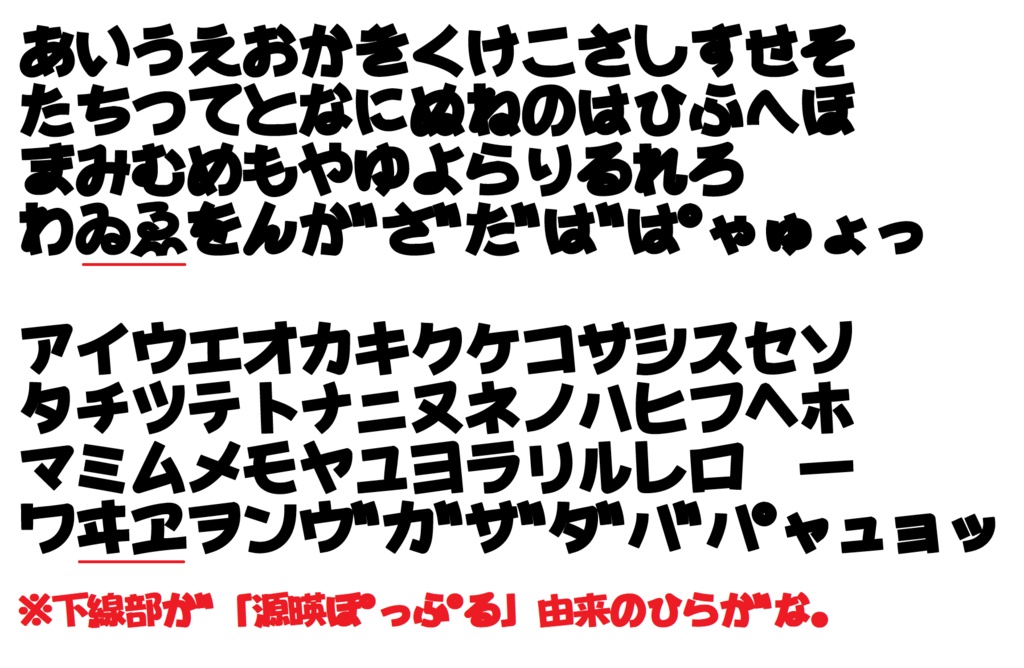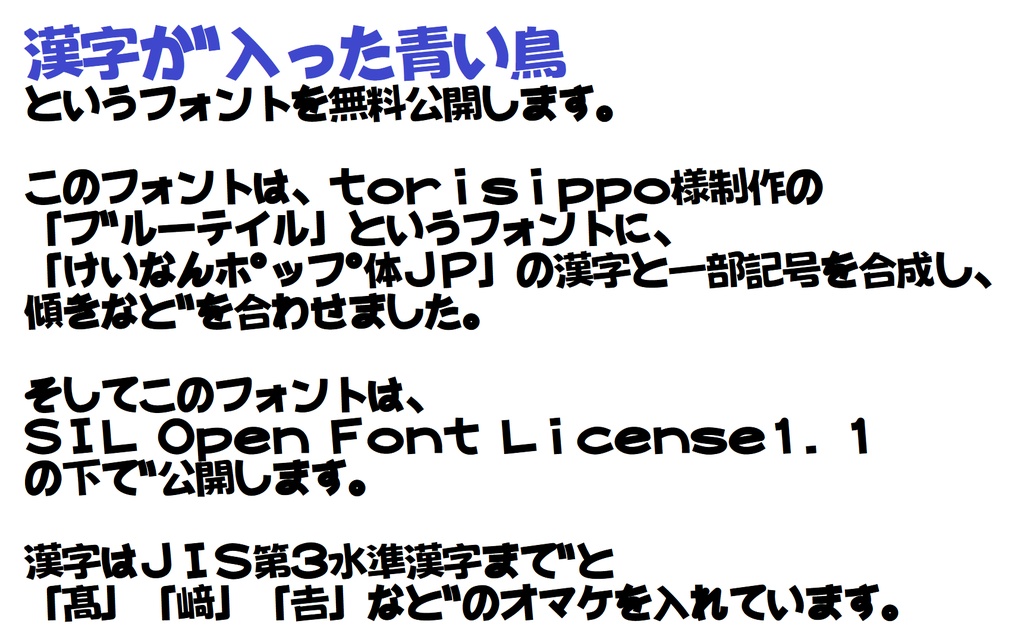
漢字が入った青い鳥M
このフォントはtorisippo様制作の「ブルーテイル」と「けいなんポップ体JP(※)」を合成し、 漢字部分を「ブルーテイル」の文字の傾きに合わせて調整したフォントです。 そしてこのフォントは、SIL Open Font License1.1の下で公開します。 ※けいなんポップ体JP:おたもん様制作の「源暎ぽっぷる」と、 中国語用フォント「荆南波波黑」を加工して、 やっちゃん様が作成した「けいなんポップ体」の漢字部分を 私、ユズノカが日本語仕様に漢字の字形を変更したり 足りない漢字を補ったりしたフォントです。 こちらも、SIL Open Font License1.1の下で公開しています。 このフォントに関しては、以下のフォントを使用、加工しています。 すべて、SIL Open Font License1.1の下で公開されているフォントです。 関係者の皆様には深くお礼を申し上げます。 ★ブルーテイル(torisippo様) https://booth.pm/ja/items/6450433 ★けいなんポップ体(やっちゃん様) https://booth.pm/ja/items/6874288 ★けいなんポップ体JP(ユズノカ:このフォントの制作者) https://mikannnoki-font.booth.pm/items/7106424 ★源暎ぽっぷる(おたもん様) https://okoneya.jp/font/genei-pople.html ★荆南波波黑(荆南字庫(Kingnam Type Foundry)様、NightFurySL2001様) https://github.com/maoken-fonts/KNBobohei SIL Open Font Licenseとは? SILライセンス原文 http://scripts.sil.org/OFL ライセンス原文日本語サイト https://licenses.opensource.jp/OFL-1.1/OFL-1.1.html ライセンスざっくり解説(たぬき侍様) https://tanukifont.com/sil/ 収録文字:ひらがな、カタカナ、英数字、(「ゐ」「ゑ」「ヰ」「ヱ」は 「源暎ぽっぷる」由来、それ以外は「ブルーテイル」そのまま) 最低限の記号、(「ブルーテイル」「源暎ぽっぷる」「けいなんポップ体JP」由来が混在) JIS第1水準漢字全部、JIS第2水準漢字全部、JIS第3水準漢字全部、 オマケの漢字:㐧髙𠮷𣘺𠩤獠𩸽戶罣喱荆卐囧閒﨓灩縉蘒﨡諼﨤靛瀞 ⻆(CJK部首補助に収録)㊙。 10月31日更新:「けいなんポップ体JP」で収録漢字の誤りが3文字ほどあり、 修正した関係でこのフォントも同じように修正し、 最初に公開した「漢字が入った青い鳥」をやめ、 Mがつく「漢字が入った青い鳥M」のみの公開としましたので ご理解をお願いしいます。